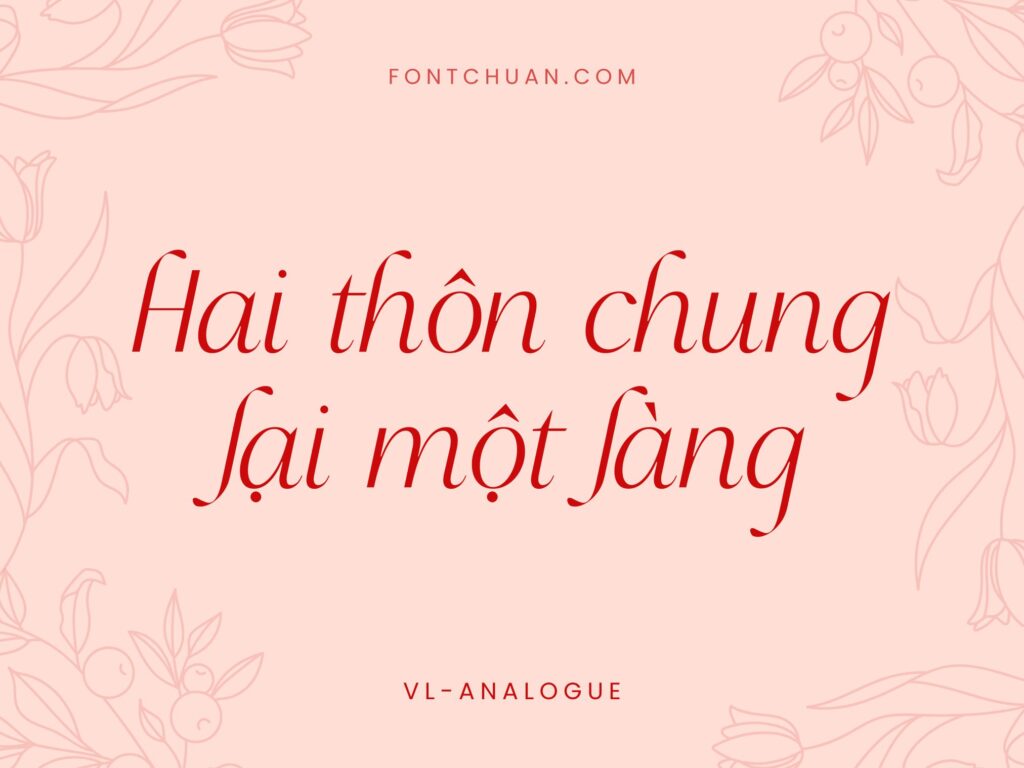
Font VL Analogue Trọn Bộ Việt Hóa
VL-Analogue là một phông chữ kết hợp giữa serif và Font Sans serif, mang phong cách hiện đại và thanh lịch. Phông chữ này có các đường cong mềm mại kết hợp với độ tương phản cao, tạo nên sự cân bằng giữa tính nữ tính và nam tính trong thiết kế. VL-Analogue đã được Việt hóa bởi Việt Linh, hỗ trợ đầy đủ các ký tự tiếng Việt, giúp người dùng dễ dàng sử dụng trong các dự án sáng tạo. Phông chữ này được thành viên Font Chuẩn sưu tầm và đăng tải nhằm phục vụ nhu cầu thiết kế đa dạng.
Với thiết kế độc đáo và linh hoạt, VL-Analogue phù hợp cho các ứng dụng như tiêu đề, văn bản, thiết kế logo, Font chữ Giáo dục và các ấn phẩm truyền thông. Trong lĩnh vực sự kiện, phông chữ này có thể được sử dụng trong các dịp như hội nghị, triển lãm và các sự kiện doanh nghiệp. Ngoài ra, VL-Analogue cũng thích hợp cho các ngành nghề như thiết kế đồ họa, truyền thông và thời trang.